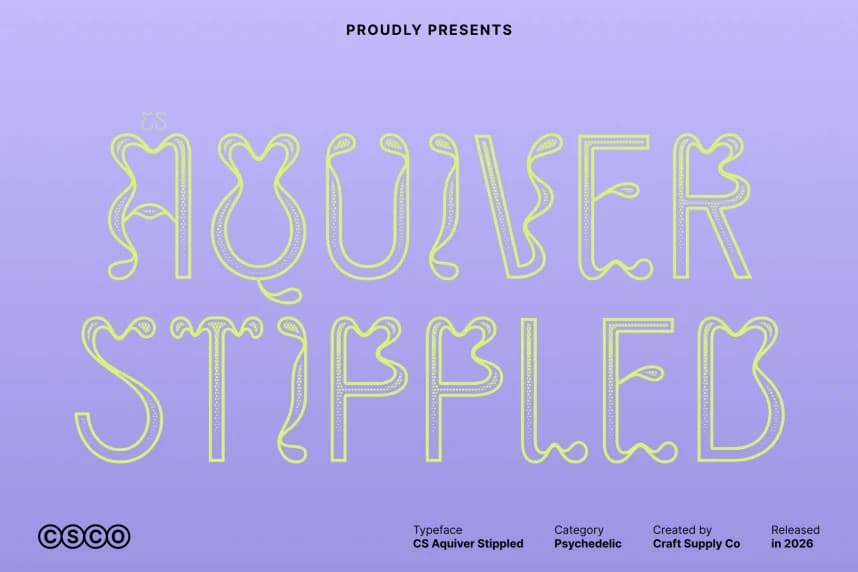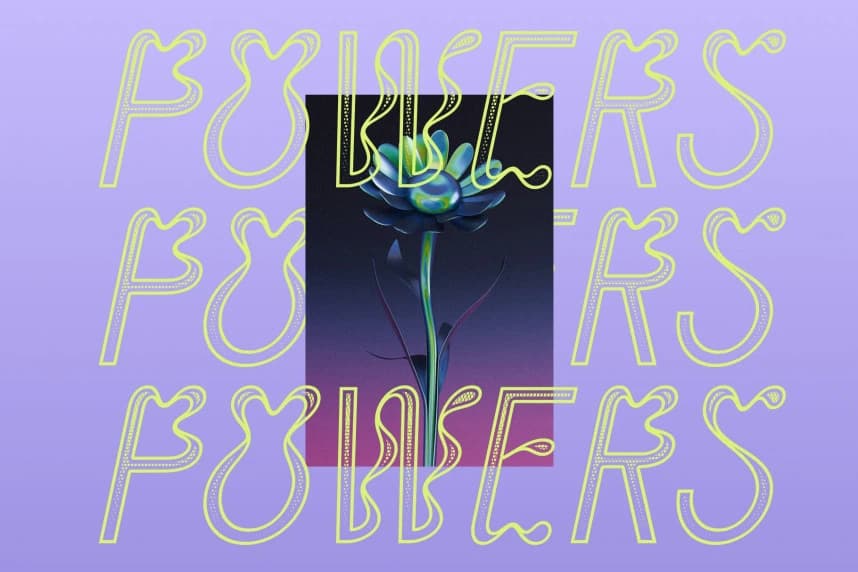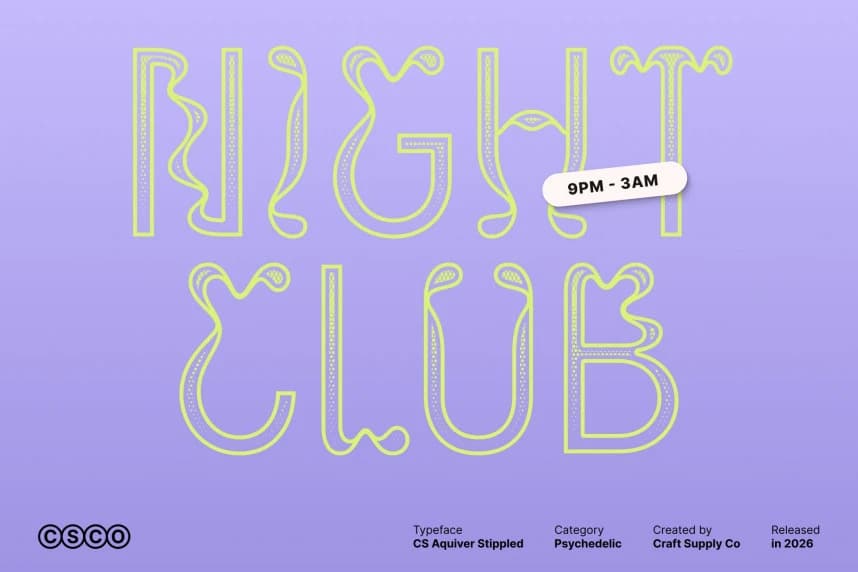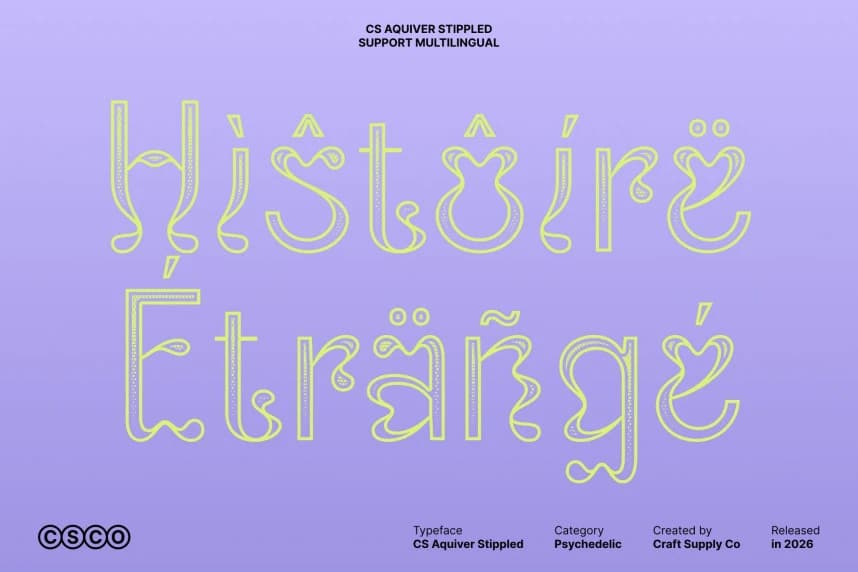
CS Aquiver Stippled Font
CS Aquiver Stippled Font – Psikedelik Gösterim Yazı Tipi, Canlı Psikedelik Tasarım, Dokulu İfade ile. Bu, canlı enerji ve cesur görsel karakterle dolup taşan bir psikedelik gösterim yazı tipidir.
CS Aquiver Stippled Font – Psychedelic Display Font Canlı psikedelik tasarım, dokulu ifade ile. Bu, canlı enerjiyle dolup taşan ve cesur görsel karaktere sahip bir psikedelik gösterim yazı tipidir.